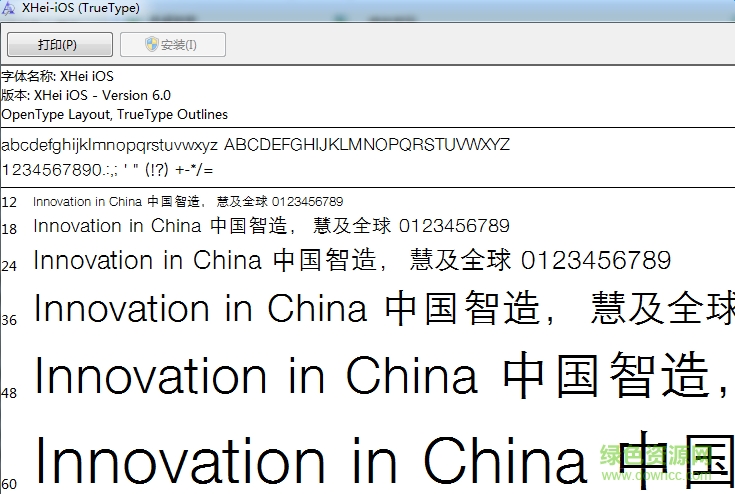
ios8蘋果手機字體
ios8字體是蘋果手機上的一款應用于手機閱讀方面的字體,該字體線條粗細適中,字型端正,簡潔大方,整體效果非常出色,能夠讓用戶在手機上更好的使用!喜歡的網(wǎng)友可免費下載收藏。
IOS8字體
ios8字體是一款本適用于蘋果手機上的字體,該字體非常適合用于閱讀,讓用戶享受更好的閱讀體驗。歡迎來綠色資源網(wǎng)下載使用